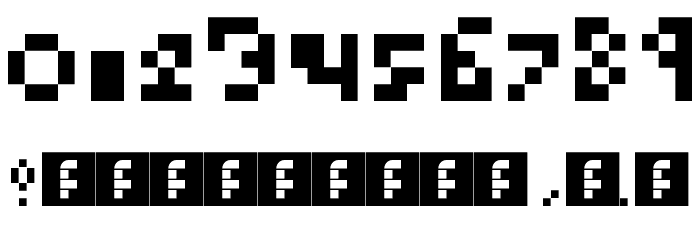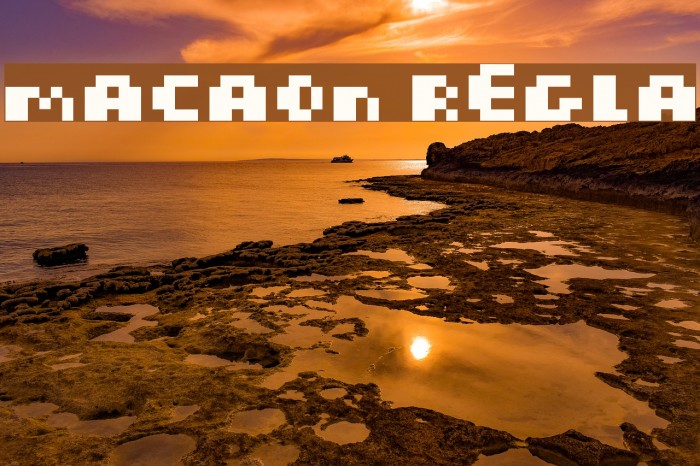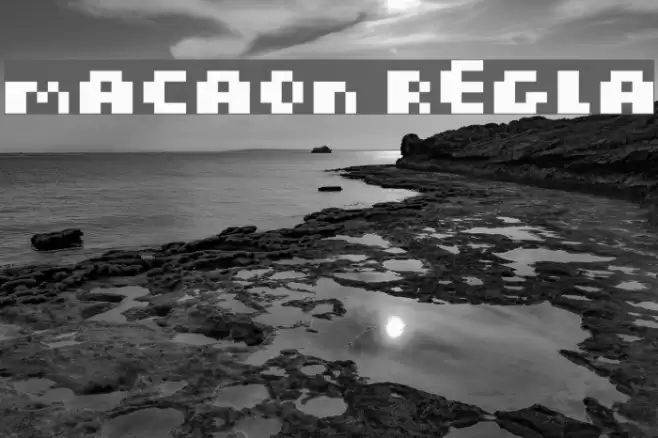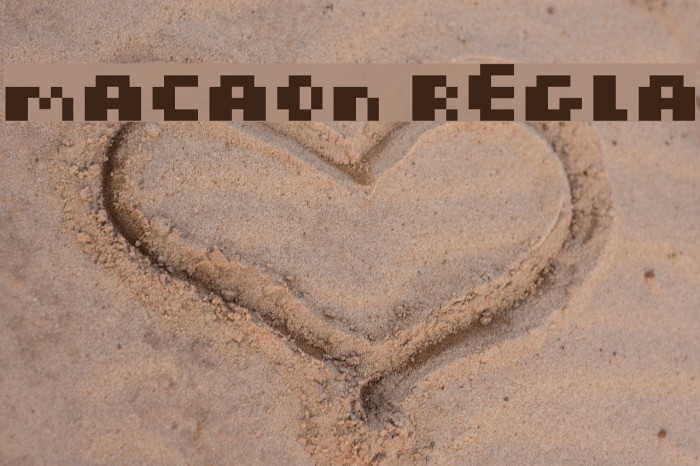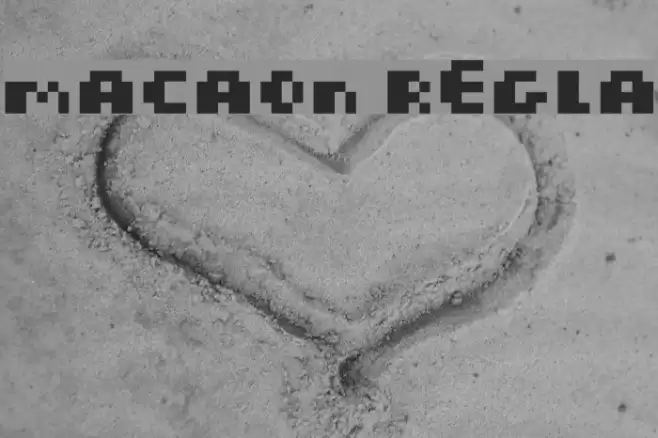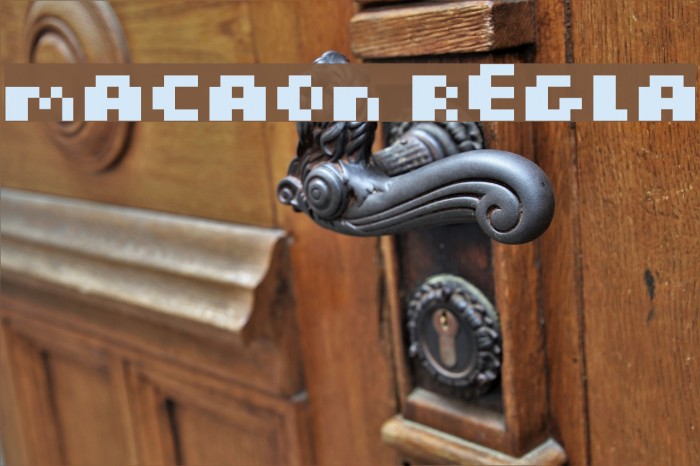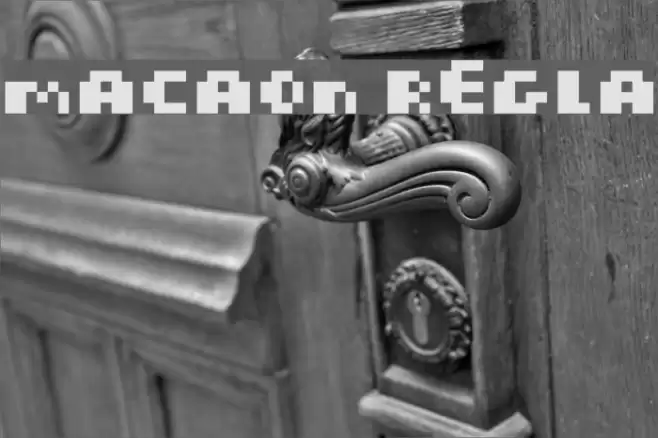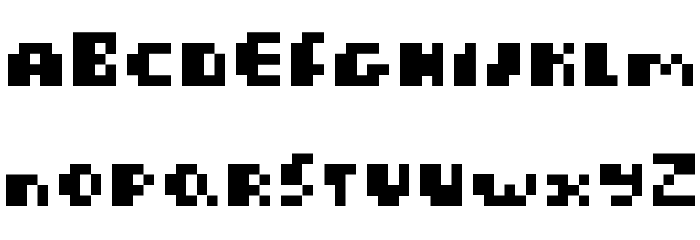
macaron Regular Font
✎ Pixel
| Stile generale | Retro, Digital |
| Progetti proposti | Ideal for video game design, tech-themed posters, retro digital art, and any project seeking a nostalgic digital look. |